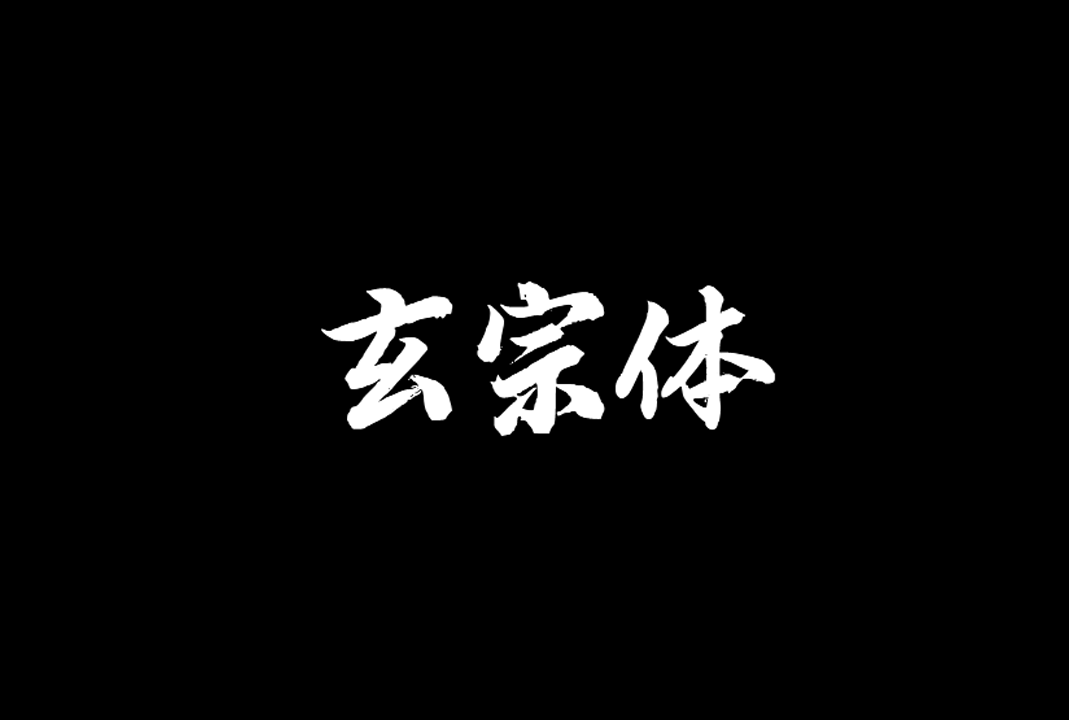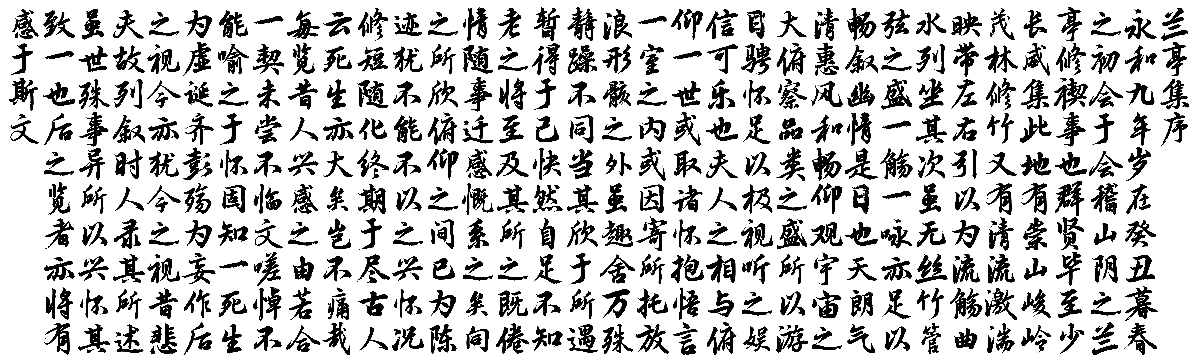
玄宗体(XuanZongTi)_免费商用中文书法字体下载
玄宗体(XuanZongTi)是一款基于唐玄宗书法《鹡鸰颂》字符创作的免费可商用中文书法字体。该字体字符经 zi2zi-JiT 生成、Potrace 矢量跟踪后,编译为 OpenType 格式字体,覆盖 GB2312 字符集 (共 6763 个汉字)。